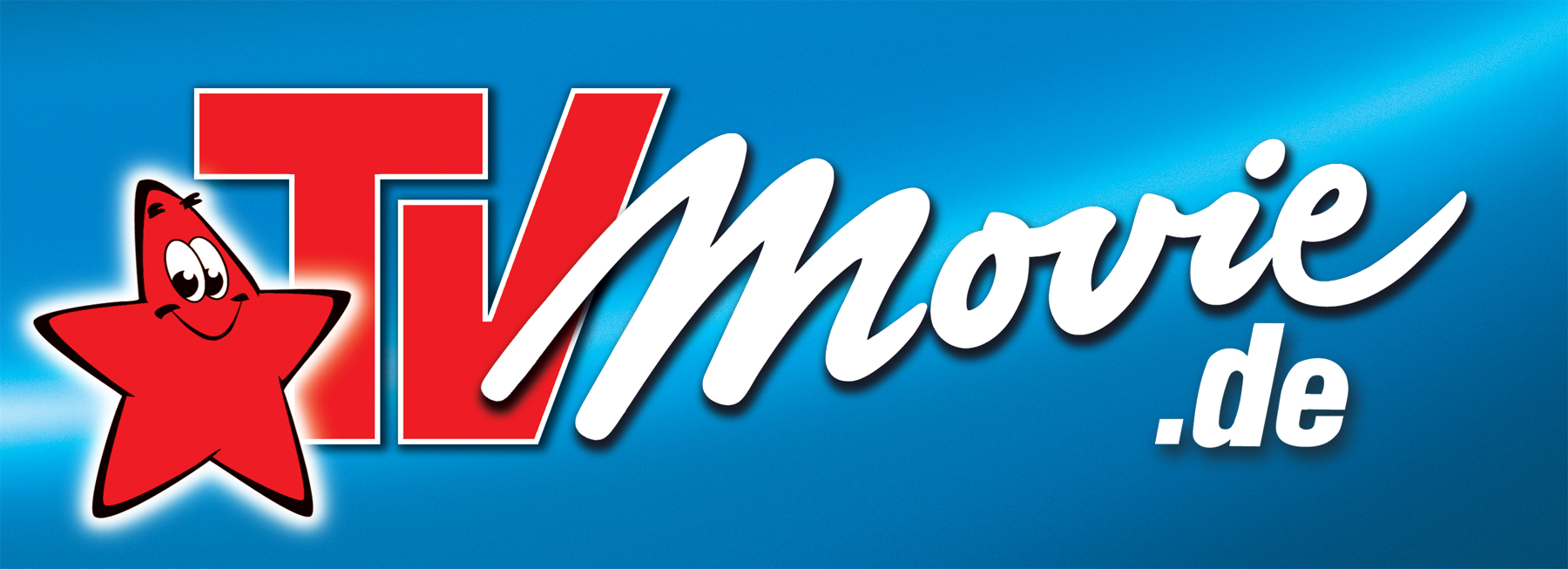
suche Schriftart der TV Movie
ich suche die Schriftart der Fernsehzeitung TV Movie
und zwar ein mal nur die des 'TV' und einmal die des 'Movie'
Das sind allesamt gezeichnete Schriftzüge.
Sicher? Hätte man dann nicht i und e besser miteinander verbunden? Das sieht so nach opentypeunfähigen Font aus ... ;-)
Okay, das ist schade weil so gut kenne ich mich dann doch nicht aus, um mir zu zumuten dass so nach zustellen...
Brauch das ganze für ein Plakat, die Aufschrift sollte Dbg Wiehl lauten...
'TV' = 'DBG' & 'Movie' = 'Wiehl'